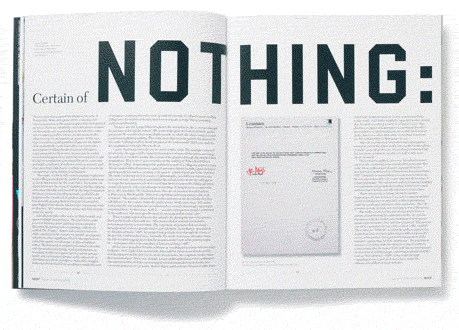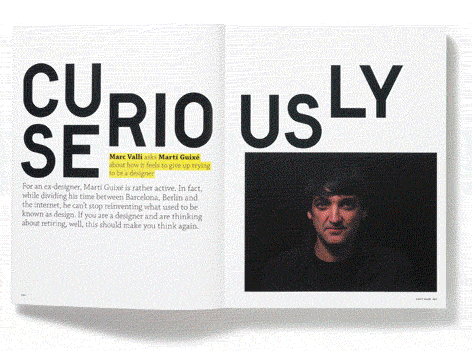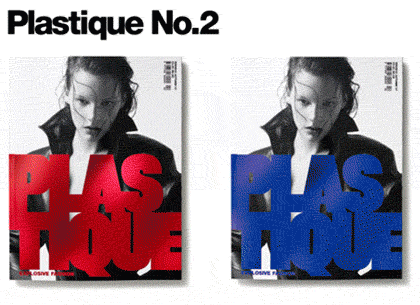
typographie des magazines de mode | le studio8design très typo
Vous savez comme je suis attaché à une réflexion sur la mise en page et la typographie des magazines de mode. Le Studio8Design apporte des réponses à cette question qui me semble fondamentale: peut-on renouveler la scénographie des magazines, prenant des risques graphiques bien au delà de ce que les ténors de la presse internationale n’osent entreprendre.
Elle, Marie-Claire, Vogue, Harper’s, autant de titres prestigieux qui fort de leur volumes publicitaires et d’une relative stabilité de leur vente en kiosque n’osent plus remuer le petit doigt pour changer un iota à leur maquette. Se faisant si l’on regarde la plupart de ces magazines, ils ont plutôt régressés en comparaison de leurs ancêtres des années 50.
Là à New York, à Paris les directeurs artistiques prenaient de vrais risques sachant toute la dette qu’ils avaient à l’encontre du monde de la Mode. Parce que le plus curieux dans cette affaire, est précisément le décalage entre les prises de risques quotidiens des créateurs de Mode et les magazines qui les relaient. Autrefois il régnaient une véritable émulation entre les deux parties. Chacun poussant l’autre à pourfendre les conventions, à les pervertir pour mieux les recréer.
Tout ceci s’est considérablement éteint pour de simples raisons financières et de structure interne aux magazines devenues de véritables machines abattre des pages et des pages sans aucune considération pour le rôle de pionnier qui doivent être le leur.